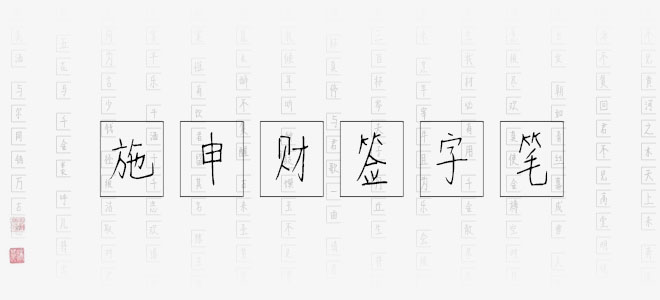
施申財(cái)簽字筆是一款極具個(gè)性的手寫(xiě)字體,字體線條粗細(xì)適中,筆畫(huà)隨性,結(jié)構(gòu)灑脫自在,具有很好的視覺(jué)感,適合于文化類(lèi)的宣傳設(shè)計(jì)、商業(yè)類(lèi)品牌的廣告和產(chǎn)品包裝設(shè)計(jì)以及個(gè)性化文字排版等較多場(chǎng)景。
施申財(cái)簽字筆